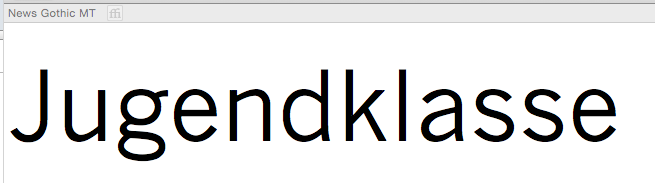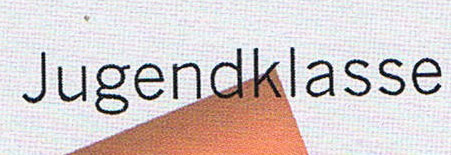
Welche Schrift ist das? (Jugendklasse)
1. News Gothic Bold
2. News Gothic
ufonts.com, ja bei bold habe ich ü; bei News Gothic aber keins (habe unter sonderzeichen auch nachgeschaut)
OK war mir nicht bewußt, was wäre sehr ähnlich unter "freien" Schriften? Ich benötige es für 2 Wörter und es muss nicht genau News Gothic sein :)
Wenn nicht auf die Franklin Gothic, dann könntest Du auch auf die relativ ähnliche und kostenfreie Source Sans von Adobe zurück greifen …
nicht furchtbar relevant:
1. News Gothic Bold
2. News Gothic
das zweite beispiel ist nicht die news gothic. ein paar details stimmen nicht, unter anderem das ohr vom ›g‹. ich vermute, dass es sich tatsächlich um die hier handelt:
nicht furchtbar relevant: das zweite beispiel ist nicht die news gothic. ein paar details stimmen nicht, unter anderem das ohr vom ›g‹. ich vermute, dass es sich tatsächlich um die hier handelt …
Die News Gothic gibt es wohl in verschiedenen Ausprägungen, wobei ich finde, dass jene News Gothic mit dem Beispiel auch bei den Ohren übereinstimmt:
Ob es diese auch wirklich ist, kann ich nicht zweifelsfrei feststellen. Mir käme aber spanisch vor, wenn die Texte nicht aus der selben Familie gesetzt worden wären.